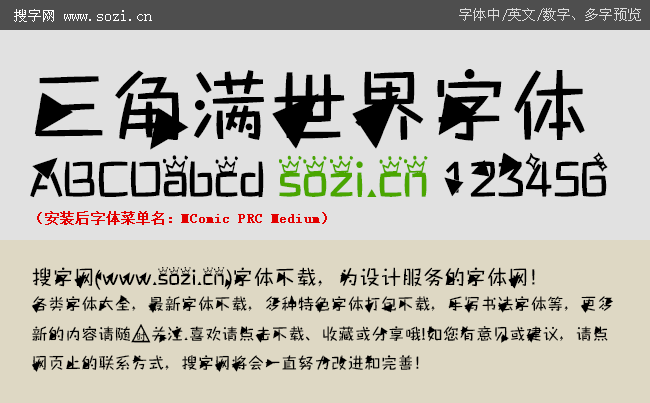
三角滿世界字體
搜字網(wǎng)給大家提供一款很有趣的手機(jī)中文字體下載。字體名字叫三角滿世界字體,這款手機(jī)字體是在方正稚藝簡體字體上加上了三角圖案。方正稚藝簡體字體在手機(jī)美化中經(jīng)常用到,這款字體非常漂亮,帶有卡通風(fēng)味,活潑而不死板,加上小三角形后更加個性,適合喜歡手機(jī)字體個性一些的朋友在手機(jī)上安裝使用。